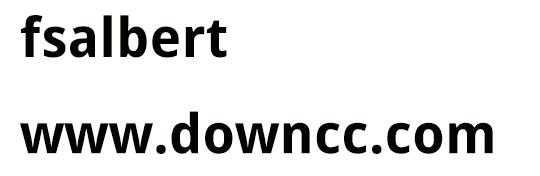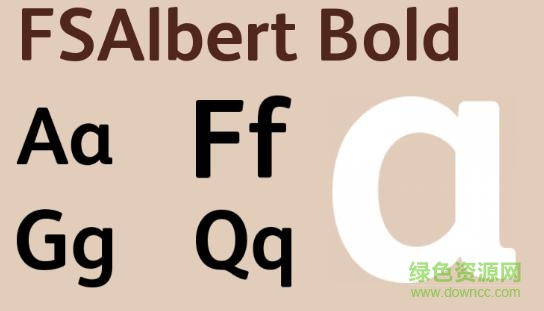
fsalbert bold系列字體是一套端正嚴謹?shù)?a href="http://kiwanis-srv.org/k/wuchenxianziti/" target="_blank">無襯線字體,結(jié)構(gòu)平穩(wěn),挺拔有力,我們平時用ppt排版或是進行網(wǎng)頁設(shè)計時都用得著,歡迎需要的朋友在本站下載!